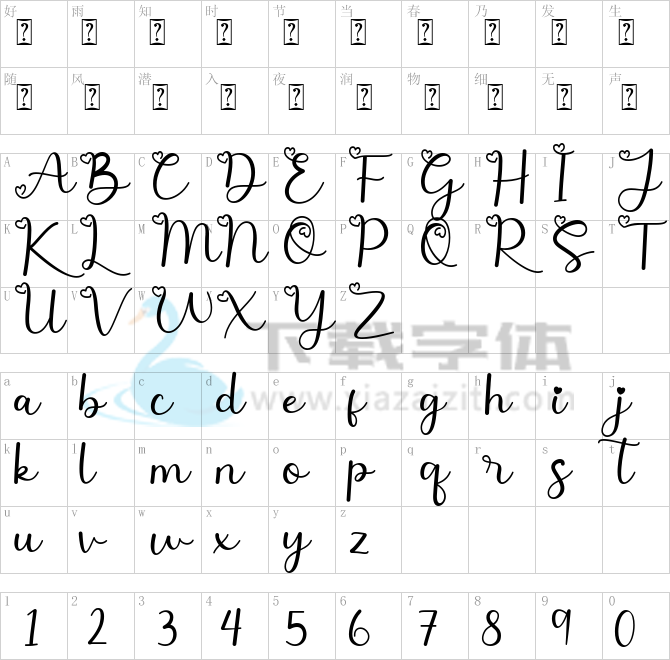
Almost Valentine.ttf字体下载,这款字体结构工整、笔画清晰,兼顾美观与易读性,适用于标题、正文、海报、包装、LOGO 等多种场景。字形优雅稳定,风格百搭耐看,适配日常排版与创意设计,让文字呈现更舒适、更具质感。Almost Valentine.ttf字体下载一笔一画,皆是细节,以均衡的比例、流畅的线条打造舒适视觉体验,字形端正大气,风格简约现代。无论是商业设计、品牌宣传还是日常排版,都能轻松驾驭,让文字更有格调与力量。Almost Valentine.ttf字体下载字体下载。